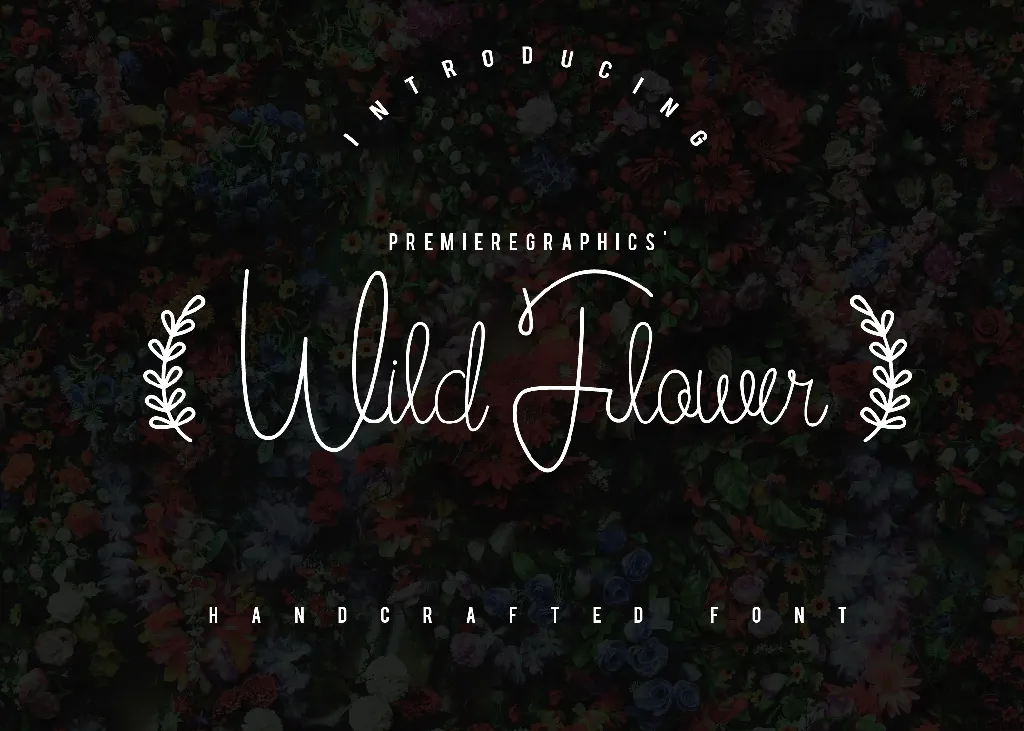
Wild Flower Script Font – Download Grátis
Saudações criativos e amantes do design! Estou procurando por uma bela escrita? Eu gostaria de apresentar a você essa maravilhosa tipografia, ela é linda e profissional. Você vai adorá-la e queremos que a acrescente ao seu catálogo de fonts para o trabalho. Introduzimos Wild Flower Script Font! Desenvolvida e compartilhada por o designer PremiereGraphics, Wild Flower Script é uma nova tipografia esculpida com suas próprias mãos! Este tipo de font é ótimo para as fotos, blogs, logotipos e marcas. Este conjunto completo está disponível para uso comercial. Se você se interessou pelo design visual e busca recursos criativos, então certamente vai adorar o Wild Flower Script Font. Ele não só trará um toque único aos seus projetos, mas também será a cara perfeita para sua marca ou blog. Aprecie as diferentes fases de desenvolvimento da plantinha até seu belo resultado final e aproveite essa oportunidade única para expandir seu conjunto de fonts com algo tão criativo e elegante como o Wild Flower Script Font. É uma ótima opção para aqueles que buscam um estilo natural e envolvente em suas criações digitais. Seja você um designer gráfico profissional, ou está apenas começando na sua jornada de design, este é sem dúvida um recurso incrível a ser adicionado à sua biblioteca. Aproveite!